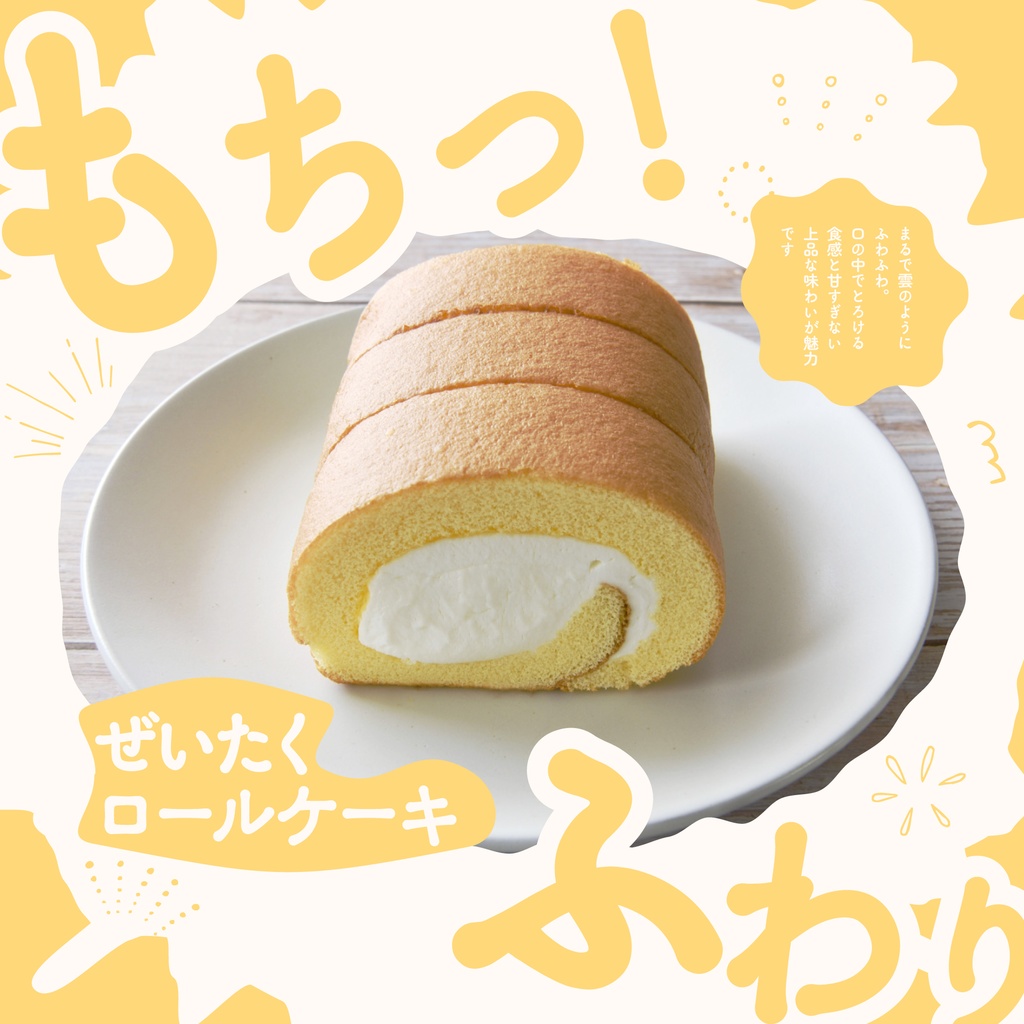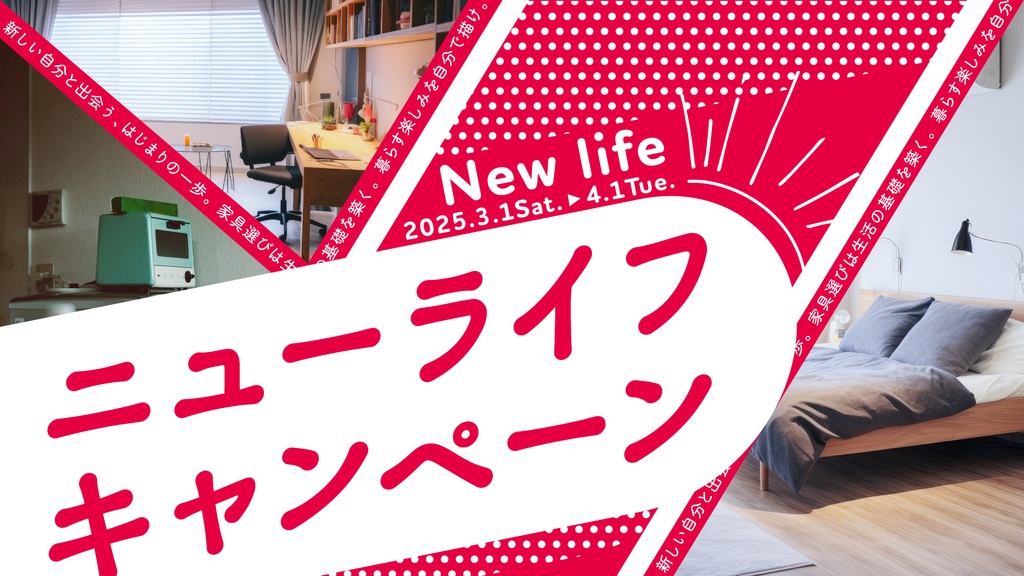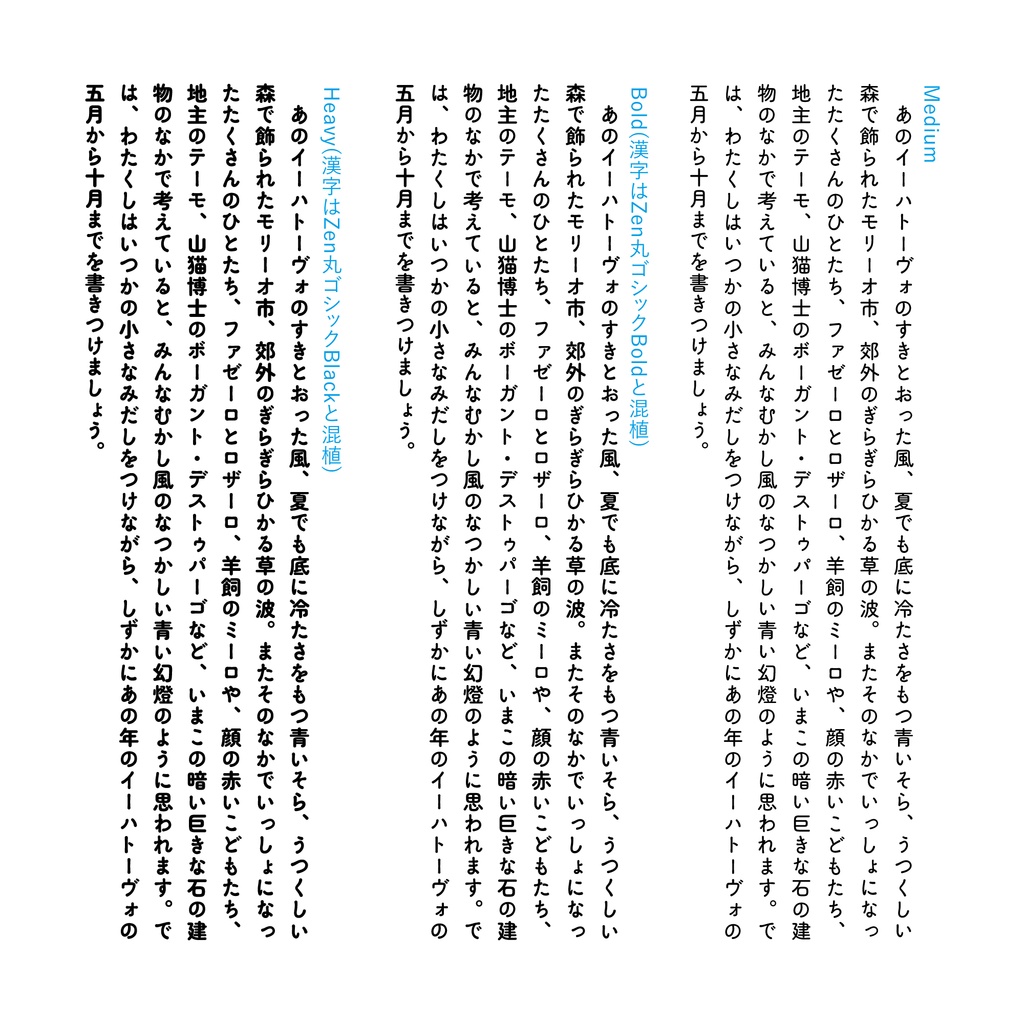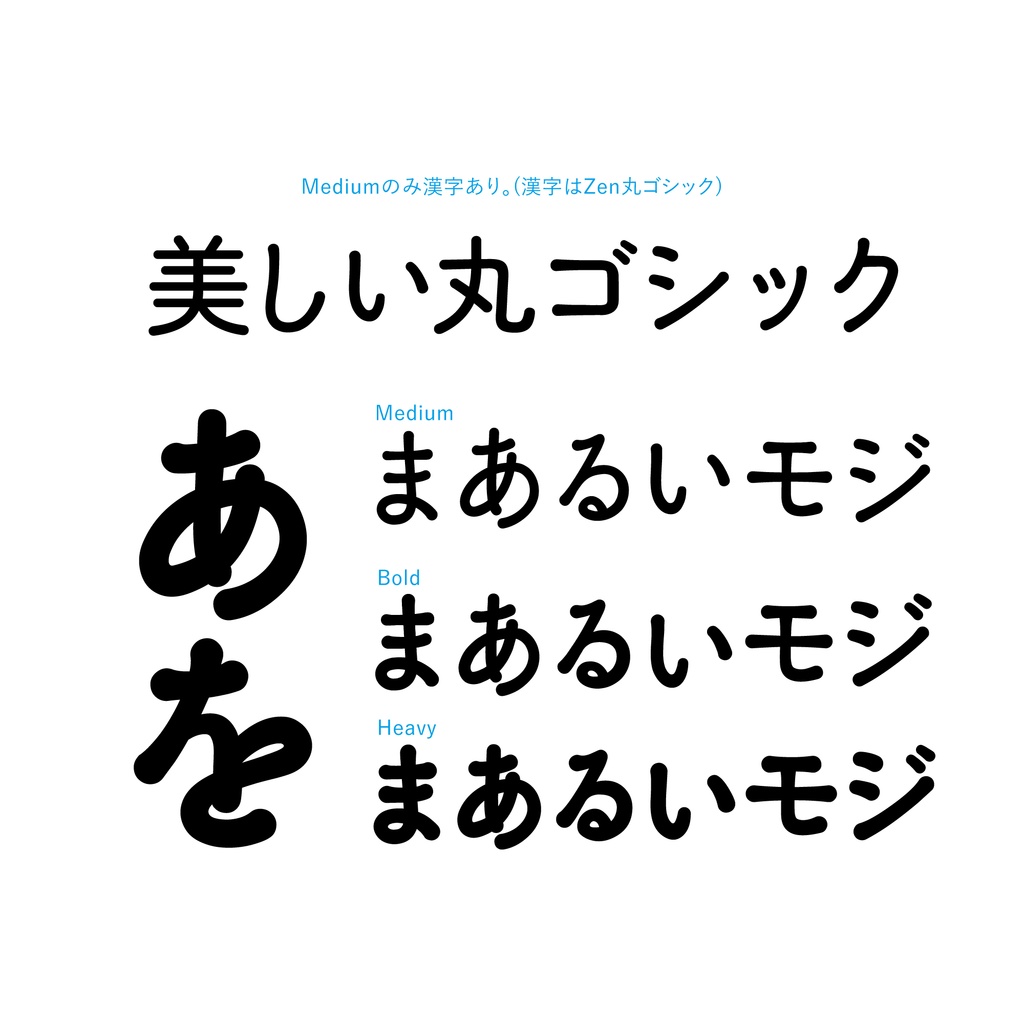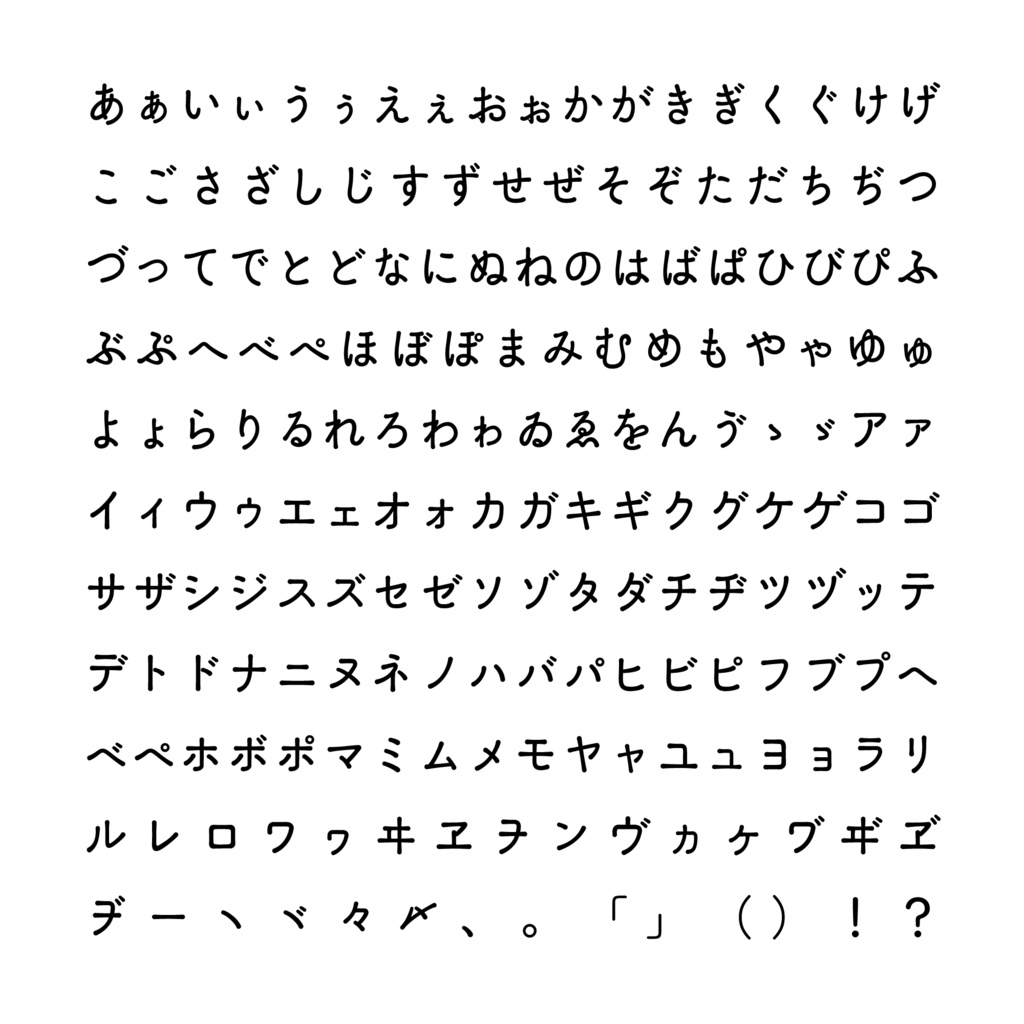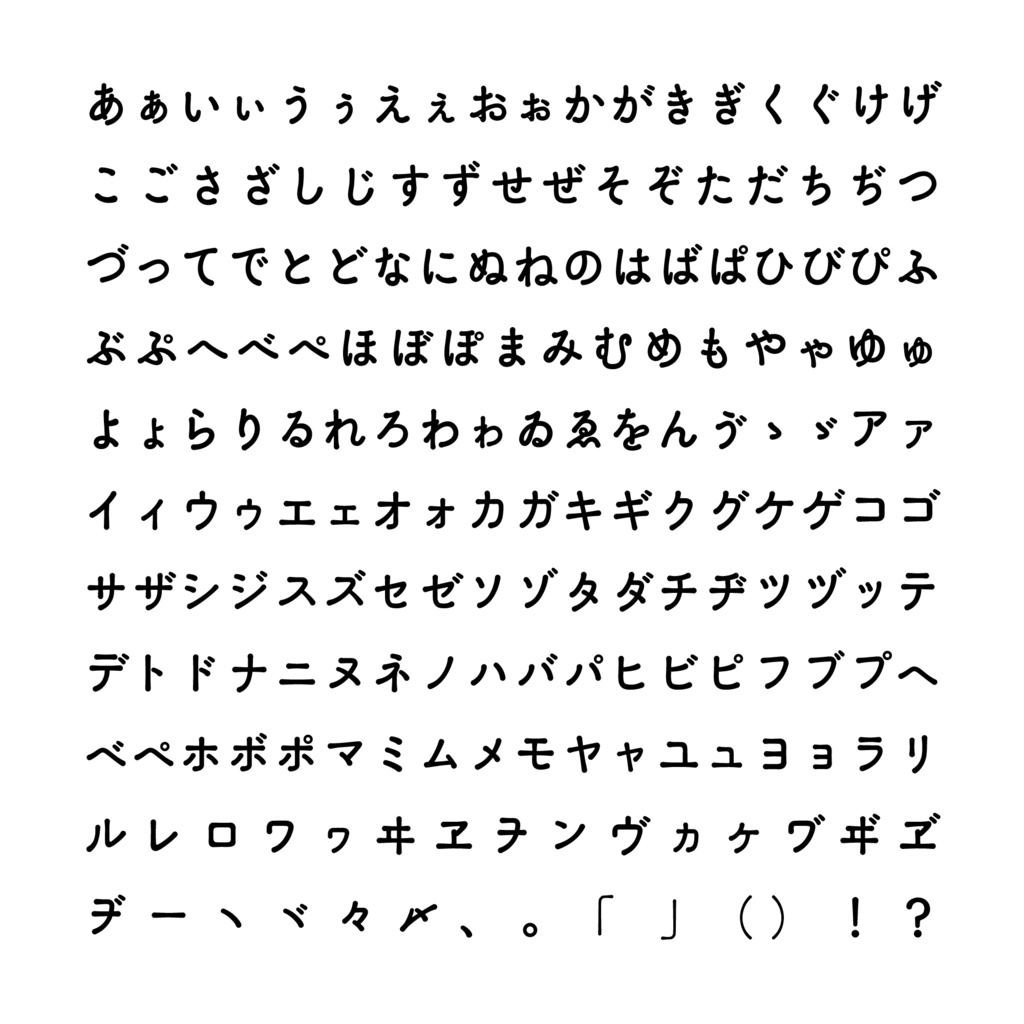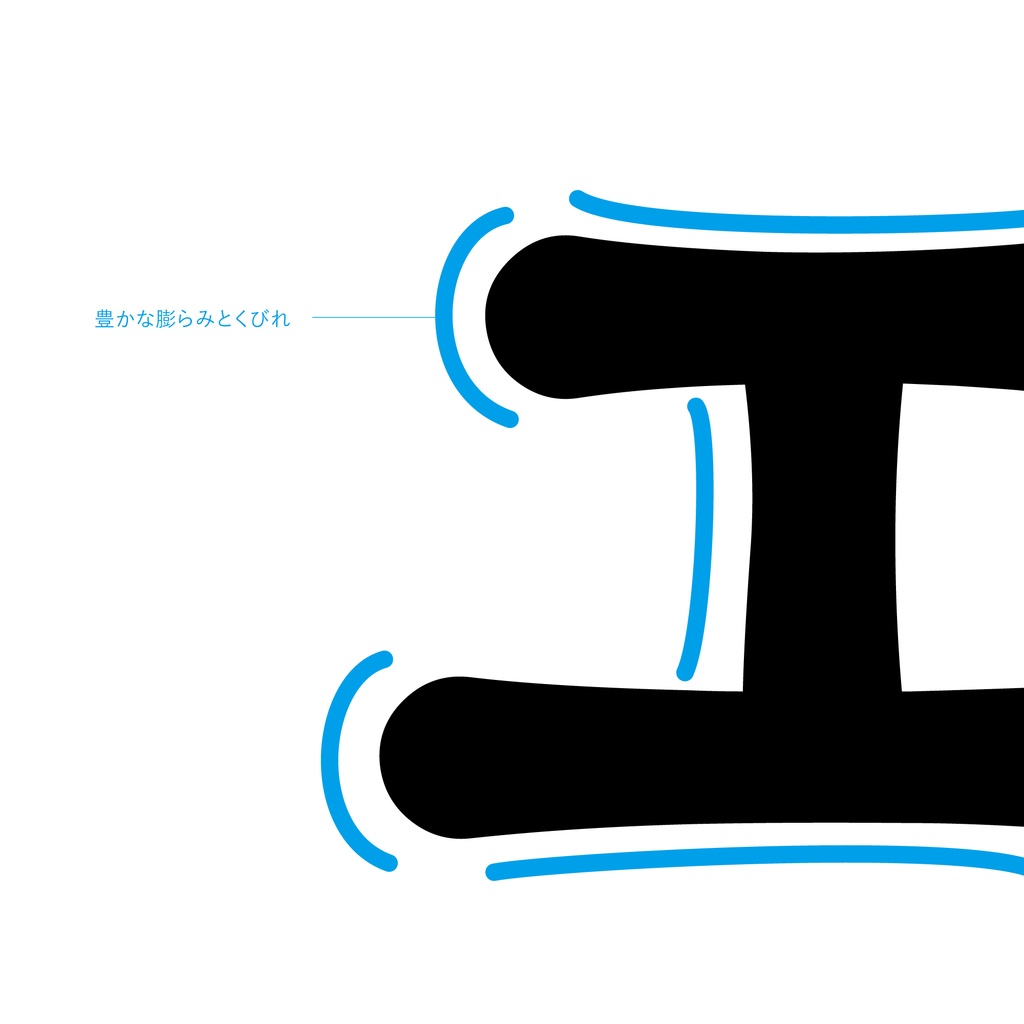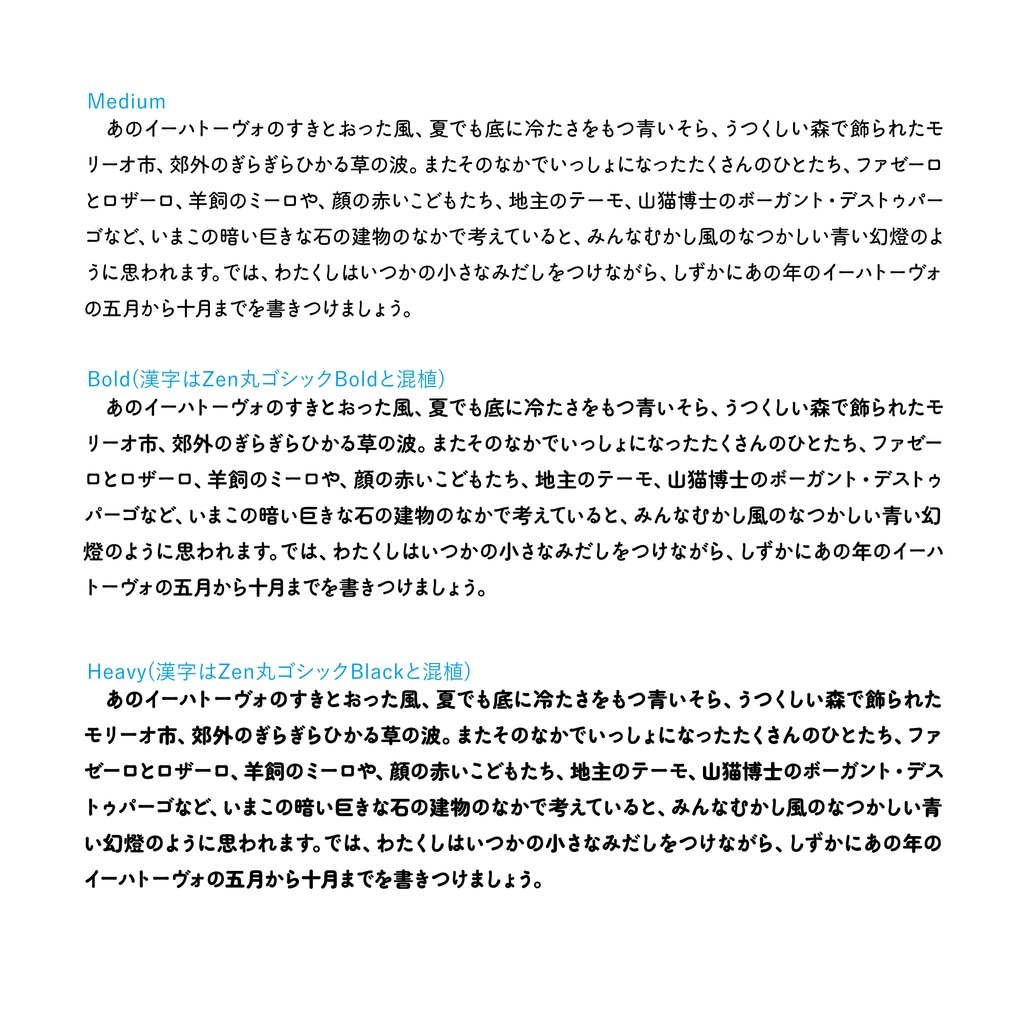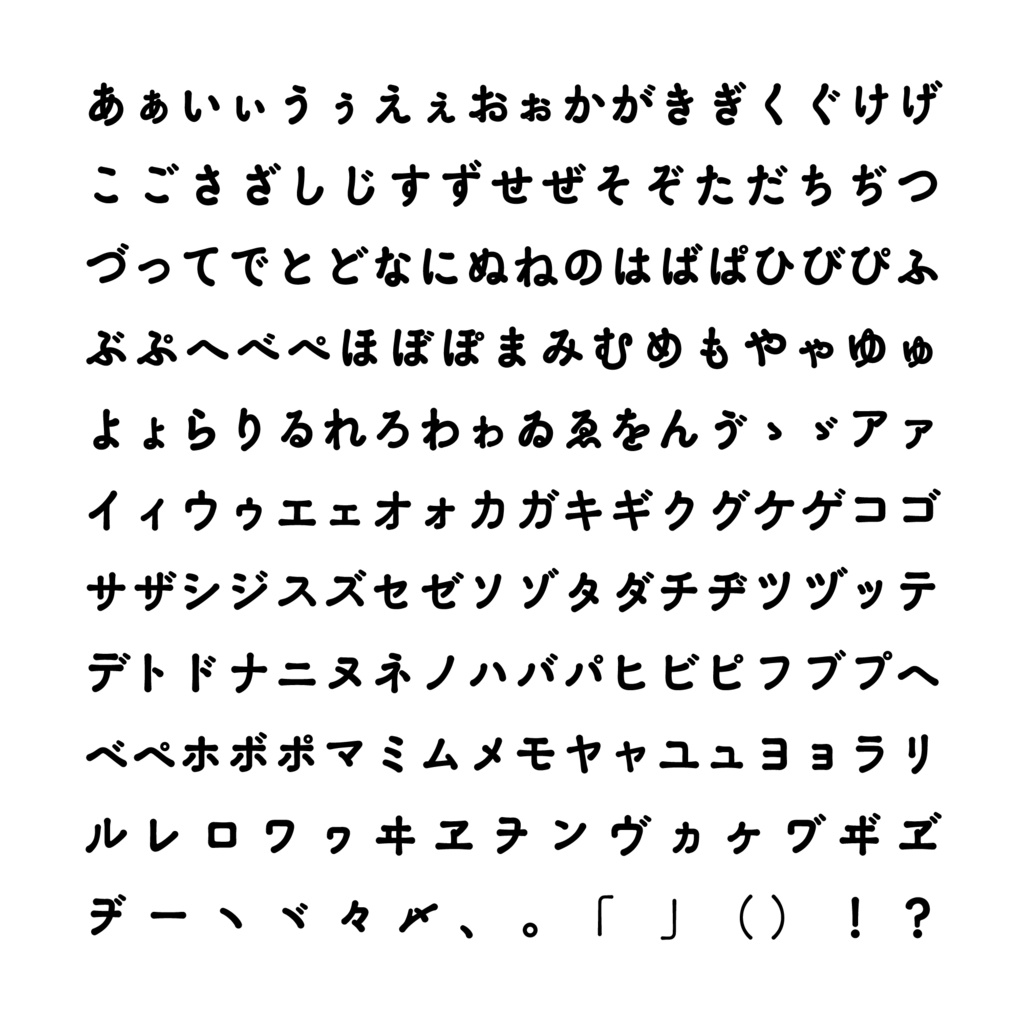
【フリー版あり】とよまーる 丸ゴシック
■書体概要 丸ゴシックの"かわいさ"に重きをおいて作っています。この書体は単に角が丸いから丸ゴシックなのではなく、丸ゴシックの持っている柔和さを「角が丸いこと」以外の要素でも表現しています。ウェイトはMedium、Bold、Heavyがあります。 Mediumはかなと一部約物を除き「ZEN丸ゴシック」から利用しています。オリジナルのフォントに深く感謝いたします。 ■フリー版と有料版の違い フリー版はウェイトMedium、漢字あり、OFLライセンス商用・個人利用可能です。 有料版はウェイトBold、Heavy、漢字なし、商用・個人利用可能です。 ■ご利用にあたり MediumはSILオープンフォントライセンスで配布、商用・個人利用可能です。 Bold、Heavyのライセンスは下記の通りです。 文字魚/Typographishのフォントデータ(以下、本ソフトウェア)は本契約に定める条件でご購入者様に使用する権利を許諾します。本ソフトウェアの著作権その他一切の権利は文字魚/Typographishに帰属します。 使用条件 1)購入者は本ソフトウェアを、本人が使用する1台までのコンピューターにインストールして使用することができます。事務所など複数人で使用する場合、コンピューターの台数分のライセンスをご購入ください。 2)印刷物に使用できます。(書籍・ポスター・看板など) 3)立体制作物に使用できます。(Tシャツ・雑貨・記事など) 4)放送・映像やWEBの制作物でアウトライン化または画像化した上で使用できます。(TV・CM・映画・DVD・ゲーム・アプリ・WEBサービス・電子書籍・動画配信・SNSなど) 5*)タイトルデザイン・ロゴマークの作成に使用できます。(*商標登録は不可) 6)Canvaなどオンラインデザイン制作ツール上にフォントをアップロードして使用することがきでます。ただし使用者1名、PCまたはタブレットなど1台の使用に限ります。 禁止事項 1)本ソフトウェアを第三者に譲渡・貸与・配布・販売することはできません。 2)本ソフトウェアを元に新たな類似または同一のフォントデータを作成すること。 3)本ソフトウェアをWEBフォントとして使用すること。 4)本ソフトウェアをハードウェアに組み込みすること。 5)本ソフトウェアを使用して商標登録をすること。 免責事項 本ソフトウェアを使用して発生した如何なる問題についても、文字魚/Typographishは責任を負わないものとします。万一、本ソフトウェアが原因で使用者および第三者に損害を及ぼしてもすべて使用者が責任を負うものとします。 保証範囲 1)本ソフトウェアに著しい誤字などが発見された場合は、修正に努め修正アップデートの情報は販売ページで告知します。修正アップデートの追加料金は不要とします。 2)本ソフトウェアのインストールに伴う技術的なサポートはいたしません。 その他 上記に記載されていない条項に関しては、著作権法及び関連法規に従うものとします。 2024/09/27 Ver1.000 公開 2024/10/03 Microsoft Officeでウェイトが選択できない問題を修正(for_officeと書かれたファイルを同梱) 2024/10/24 有料版のライセンスを更新 Copyright (c) 2024 Typographish All Rights Reserved.